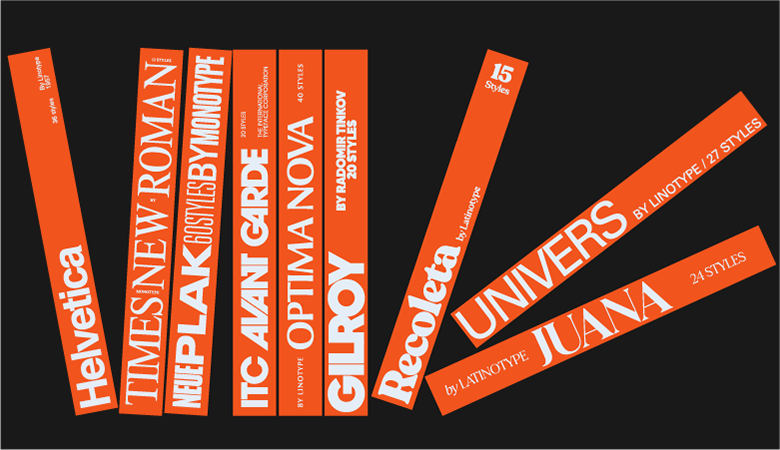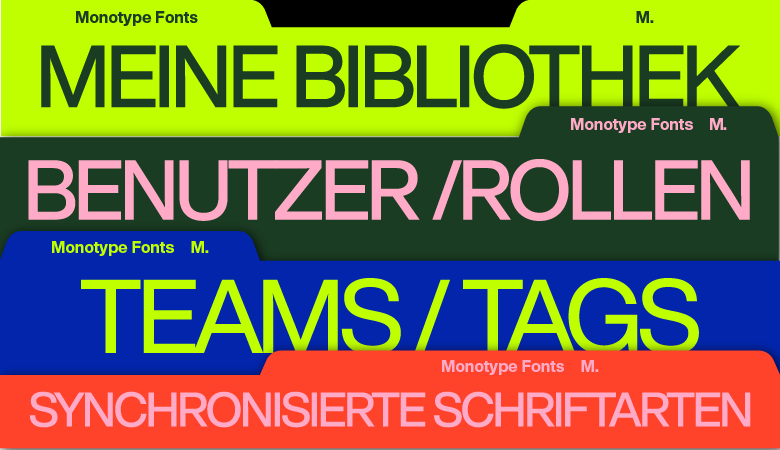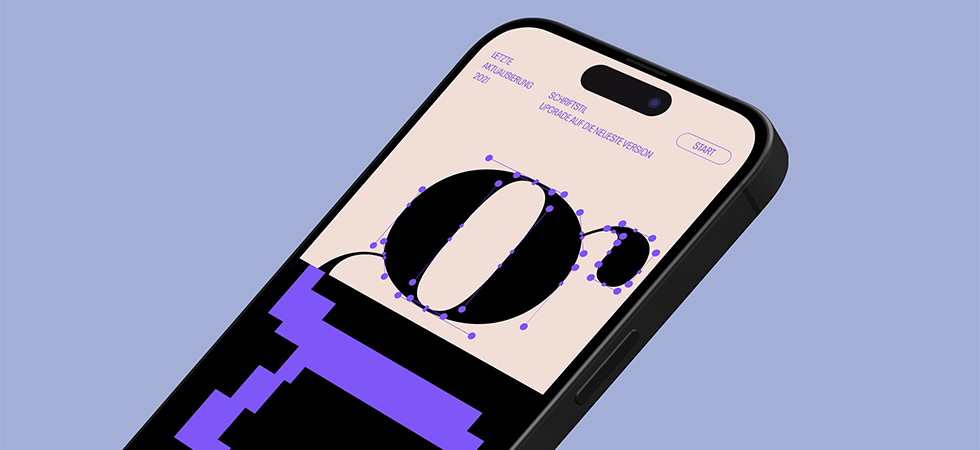
Die transformative Kraft der Schrift: Wie die richtige Typografie Web- und App-Design revolutioniert
Marken kämpfen um Aufmerksamkeit und jedes Element zählt. Die Schrift ist dabei ein oft übersehenes Detail, obwohl sie großen Einfluss auf den Erfolg eines Unternehmens, die Markenentwicklung und die digitale Transformation haben kann.
Konstante für sich immer weiterentwickelnde Marken: die richtige Schrift. (Bild: Monotype)
Um die Relevanz der Schriftauswahl zu unterstreichen, bietet sich ein Zitat von Monotype-Creative-Type-Director Charles Nix an: „Markenbildung ist immer in Bewegung. Es gibt keine statischen Marken.“ Und um einer sich immer weiterentwickelnden Marke eine starke Konstante zu geben, die sie im digitalen Raum wiedererkennbar macht, braucht es gute Typografie.
Marken schaffen Vertrauen, stiften Identität – und sorgen so dafür, dass Kund:innen zu ihnen zurückkehren. Eine einheitliche Schrift transportiert dieses Vertrauen in stabile Markenwerte und ist als konstante visuelle Stimme des Unternehmens jederzeit im Einsatz.
Die richtige Schriftwahl ist außerdem entscheidend, um die Markenentwicklung langfristig zukunftssicher zu machen. Warum das so ist und was Schriftplattformen damit zu tun haben, liest du hier.
Schriften und Markenerfolg: Warum die richtige Wahl entscheidend ist
Die richtige Schriftauswahl ist entscheidend für den Erfolg einer Marke, sowohl digital als auch offline, da die Lesbarkeit direkt die Benutzer:innenerfahrung beeinflusst. Eine gut lesbare Schrift erleichtert den Kund:innen und Leser:innen das Erkennen des Textes und erhöht damit die Interaktion und Verweildauer auf der Website oder in der App.
Ungeeignete Schriften können nicht nur die Benutzer:innenerfahrung und damit die Markenidentität beeinträchtigen, sondern auch zu längeren Ladezeiten und fehlenden Zeichen führen, was die Expansionen in neue Märkte behindern kann. Zudem führt der Kauf einzelner Fonts für Designer:innen oft zu Lizenzproblemen, was nicht selten Zeit und Geld kostet.
Das ist für jede Art von Unternehmen und Marke relevant – ob in Form einer erneuten Interaktion, einer Buchung oder eines Kaufs. Die verschiedenen Herausforderungen rund um die Schriftauswahl können somit weitreichende Folgen für die Markenreputation und die Effektivität des Designs haben.
Die Wahl der richtigen Schrift ist keine leichte und sollte wohlüberlegt sein. (Bild: Monotype)
4 Eigenschaften einer erfolgreichen Schrift
Für eine erfolgreiche Website oder App ist die richtige Schrift keine Nebensache. Die vier wichtigsten Eigenschaften von Schriften im digitalen Raum sind:
• Lesbarkeit
• Konsistenz
• Performance
• Langlebigkeit
Lesbarkeit
Gut lesbare Schriften sind für Leser:innen vor allem eines: nicht störend. Sie sind leicht zu erfassen und für das Gehirn schnell zu erkennen, sodass Leser:innen Inhalte problemlos aufnehmen können.
Konsistenz
Die Schrift einer Marke ist wie ihre visuelle Stimme – und damit diese auch wiedererkannt wird, muss ein konsistentes Erscheinungsbild sichergestellt werden. Konsistent meint dabei aber nicht statisch; die Schrift kann eine starke einheitliche Identität transportieren und trotzdem flexibel anpassbar sein.
Performance
Wie jedes andere lizenzierte Designelement sollte auch die Schrift gründlich evaluiert und bewertet werden, um sicherzustellen, dass die endgültige Auswahl alle Funktionen erfüllt und die Qualität bietet, die erwartet wird.
Langlebigkeit
Um bei zukünftigen Rebrandings entspannt bleiben zu können, sollte die gewählte Schrift alle Sprachen und Zeichen enthalten, die aktuell gebraucht und möglicherweise in naher Zukunft benötigt werden. Ein guter Anlaufpunkt dafür sind etablierte Schrifthersteller und -plattformen, die bei technischen Problemen, Sonderzeichenwünschen und anderen Supportanfragen schnell reagieren und dafür sorgen, dass die Fonts in jeder Web- und App-Umgebungen einwandfrei funktionieren.
Plattform versus einzelne Schriften
Apropos Schriftplattformen: Beim Kauf einzelner Schriften kann es passieren, dass beispielsweise nicht alle benötigten Sonderzeichen verfügbar sind oder Lizenzprobleme auftreten. Die Art und Weise, wie Designer:innen Fonts erwerben, hat also einen großen Einfluss auf den Designprozess und alle damit in Berührung kommenden Abteilungen.
Monotype Fonts: Zuverlässiges und sicheres Font-Management
Monotype Fonts ist das Vollabonnement für die größte Schriftbibliothek und eine zentrale und umfassende Lösung, die das typografische Gestalten sowie das Verwalten und Lizenzieren von Fonts nahtlos miteinander verbindet. Nie war es einfacher, mit den besten Schriften der Welt zu arbeiten.